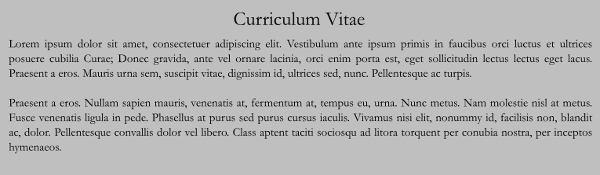
Sering Ditolak? Coba Pake Font Ini Untuk CV Lamaran Kerja Kamu!
Jika kamu mencari lowongan pekerjaan dengan mengajukan Lamaran Kerja atau Curriculum Vitae (CV) ke perusahaan ini-itu, namun belum juga dipanggil buat interview/wawancara karena alasan tertentu. Mungkin salah satu alasannya karena penggunaan font yang kurang tepat dan terlihat tidak professional yang berpotensi lamaranmu tidak diterima. Jadi, saya rangkum beberapa font yang bisa kamu gunakan dalam membuat CV yang terkesan professional.
Berikut ini beberapa font yang wajib kamu coba dalam membuat lamaran kerja:
1. Helvetica
Huruf Helvetica adalah huruf yang paling tepat digunakan ketika menulis surat lamaran dan CV. Jenis huruf Helvetica merupakan huruf yang sederhana, tidak rumit, tapi mengesankan profesionalitas; jujur, dan ringan.
**2. Garamond **
Selain Helvetica, Garamond juga salah satu huruf yang disukai dalam keperluan profesional karena mudah terbaca, nggak bikin mata sakit walaupun berukuran kecil dan tipis.
3. Didot
Kamu yang ingin bekerja di industri kreatif wajib menggunakan jenis huruf yang mencerminkan kreativitasmu, contohnya jenis huruf Didot. Didot merupakan jenis huruf yang indah, tinggi, dan sedikit feminin. Terkesan ramping dan cocok banget digunakan untuk melamar kerja di industri kreatif.
Selain dari ketiga jenis font tersebut, masih banyak font alternatif lainnya yang bisa kamu gunakan seperti Noto Serif, Rekha, dan Product Sans. Jadi kamu pakai jenis huruf apa, guys?